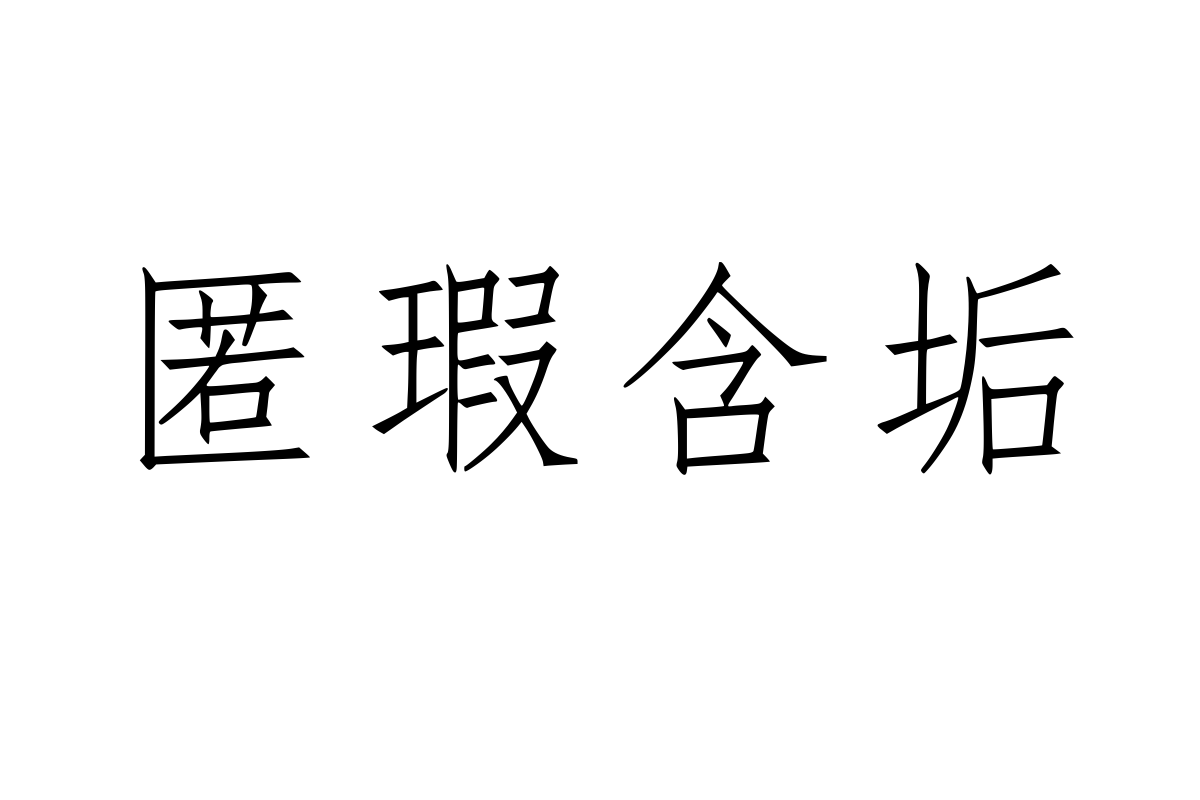
兰米仿宋繁简字体是一款由设计师精心打造的中文字体,它结合了仿宋和繁体两种风格,旨在为用户提供更加丰富多样的视觉体验。这款字体具有以下特点:
1. 字形优美:兰米仿宋繁简字体采用了独特的字形设计,使得文字看起来更加美观大方。无论是在正式场合还是日常使用,都能展现出专业而优雅的气质。
2. 易于识别:这款字体的字形清晰易读,无论是在印刷品还是电子屏幕上,都能保证文字的可读性。这使得兰米仿宋繁简字体成为了各种应用场景的理想选择。
3. 适用范围广泛:兰米仿宋繁简字体适用于各种类型的文本,包括标题、正文、广告等。无论你是需要进行商业宣传还是个人创作,这款字体都能满足你的需求。
4. 个性化定制:兰米仿宋繁简字体提供了多种字重(如粗体、细体、斜体等)和字形样式供用户选择,让你可以根据自己的喜好和需求进行个性化定制。
总之,兰米仿宋繁简字体是一款功能强大、适用范围广泛的中文字体,无论是在设计、出版还是其他领域,都是一个值得推荐的选择。